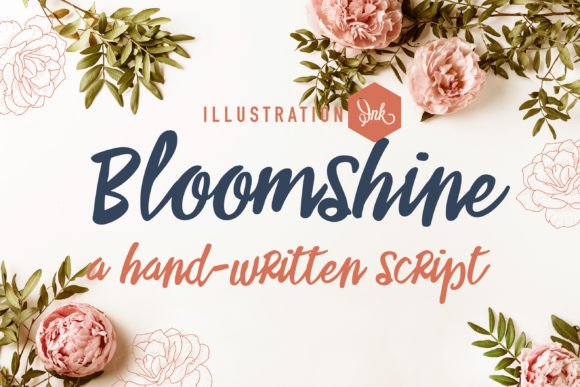
Bloomshine
適切なデザイン要素を見つけるのは難しい場合がありますが、Bloomshineは作品を即座に引き立てる優れたコレクションを提供します。
POD(オンデマンド印刷)製品、結婚式の招待状、またはソーシャルメディアのグラフィックを作成している場合でも、Bloomshineは理想的です。